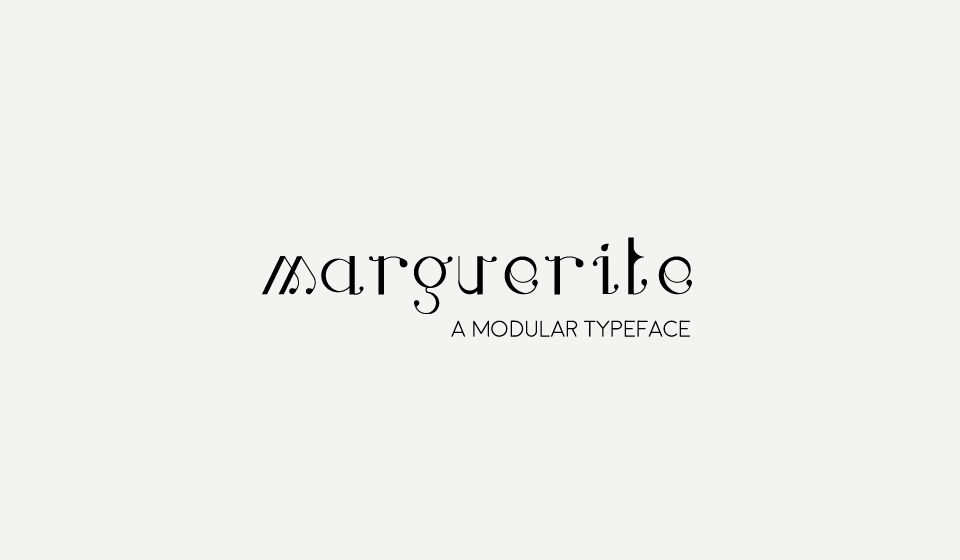
A ‘Marguerite Typeface’ é uma escolha elegante para qualquer projeto que valorize os elementos manuscritos e a personalidade única do Blackletter Font. Desenvolvida pelo designer Hamilton, essa fonte oferece um conjunto de linhas firmes e rígidas, característica típica dos tipos serifados na categoria Blackletter. Com uma paleta de traços finos que se torna mais espessos conforme avança na palavra, a ‘Marguerite Typeface’ destaca-se por seu charme único e sua capacidade de criar um texto enigmático ou sofisticado. Seja para contratos legais, obras literárias ou elementos gráficos de revistas históricas, esta fonte é perfeita para quem busca uma harmonia entre modernidade e tradição na escrita.